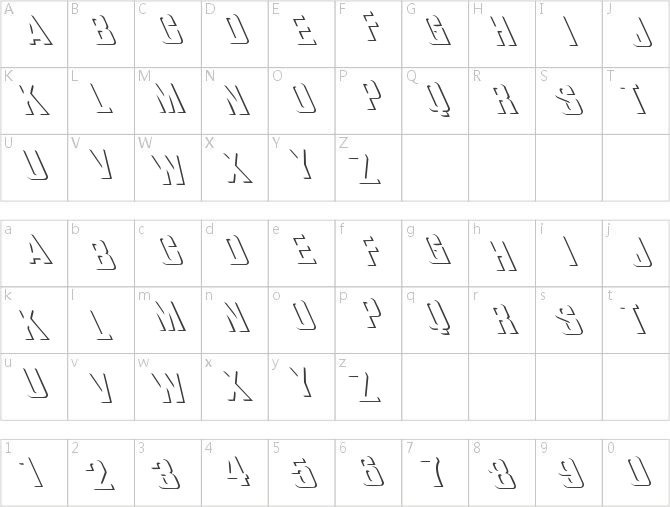
What A-Relief Extreme Lefti
What A-Relief Extreme Lefti介绍
What A-Relief Extreme Lefti字体字库是一款让人赏心悦目、百看不厌的英文字体,适合各类广告和产品包装设计应用,字体大小0.03MB,格式为ttf字体,上传用户是welking,作者/版权方为未知